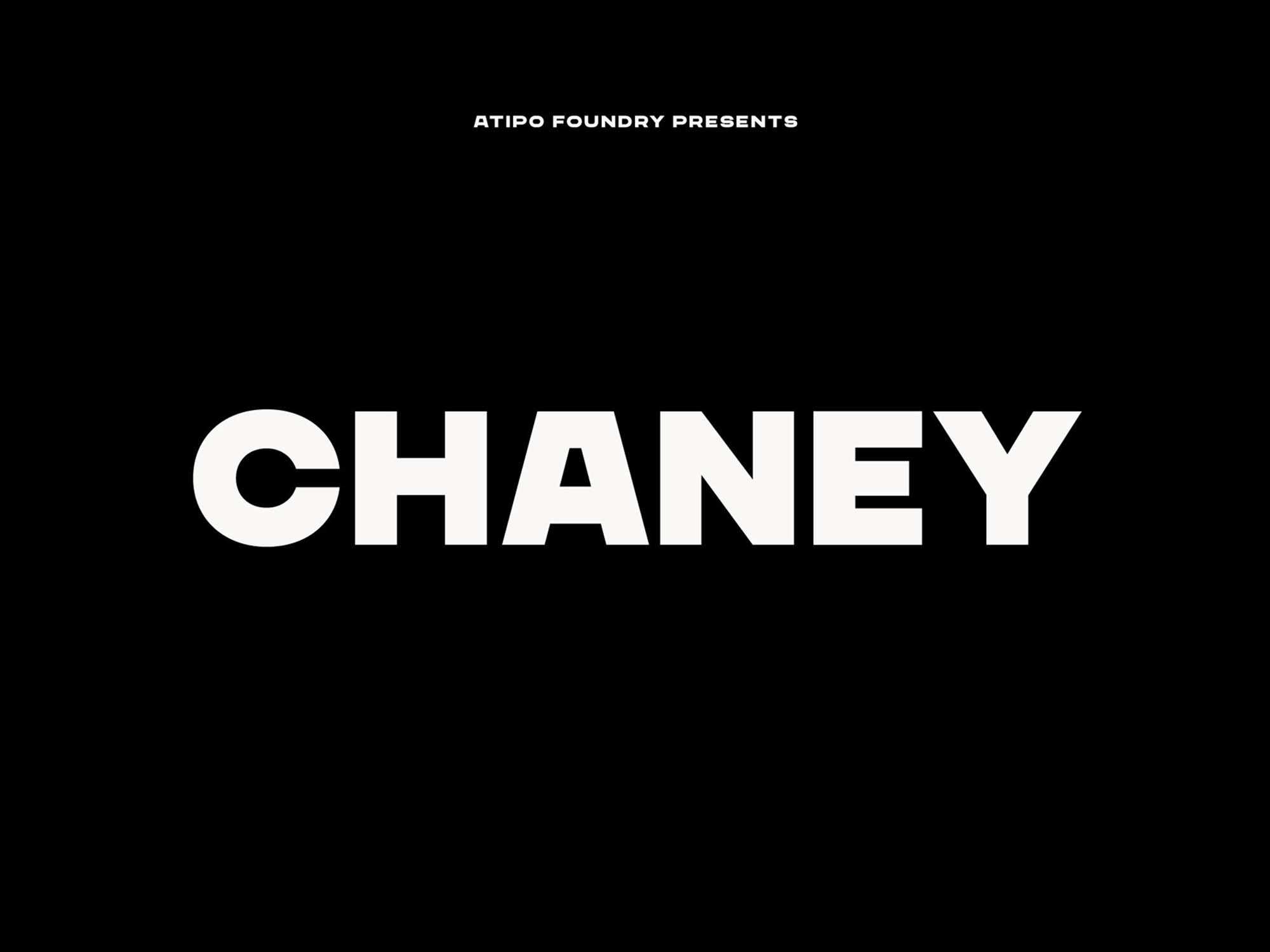
Na categoria de mockups, o recurso ‘Chaney Sans Font’ é uma ferramenta poderosa para designers de todas as habilidades. Esse é um font que oferece uma ampla variedade de aparências, uma característica que o torna extremamente versátil e adaptável a diversos projetos. Este font, chamado Chaney, é uma criação de Atipo Foundry e pode ser facilmente incorporado a qualquer projeto. Seu estilo forte e a variedade de caracteres o tornam ideal para criar um impacto chamativo em campanhas de marketing, logotipos, materiais de fãs, anúncios impressos e online, e até mesmo em textos informativos. Com apenas alguns cliques, você pode incorporar Chaney à sua coleção e aproveitar todos os seus recursos para tornar seus projetos ainda mais atraentes e memoráveis.